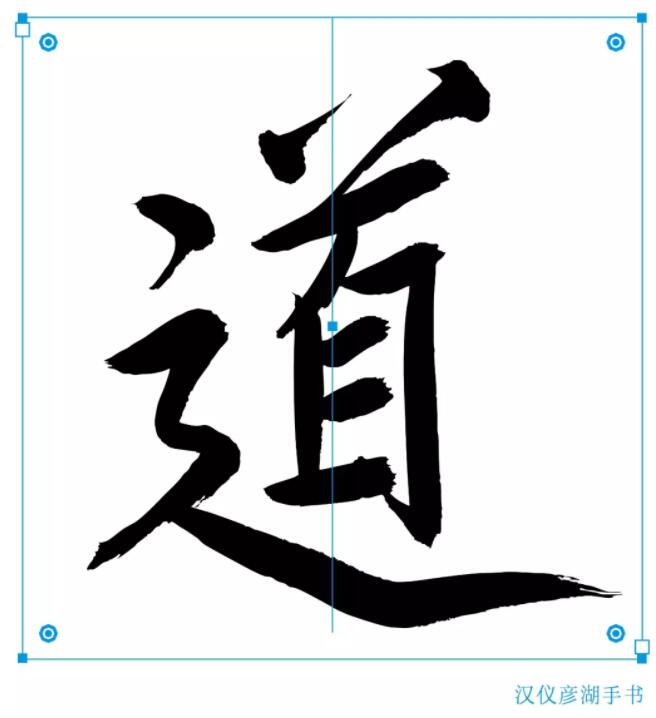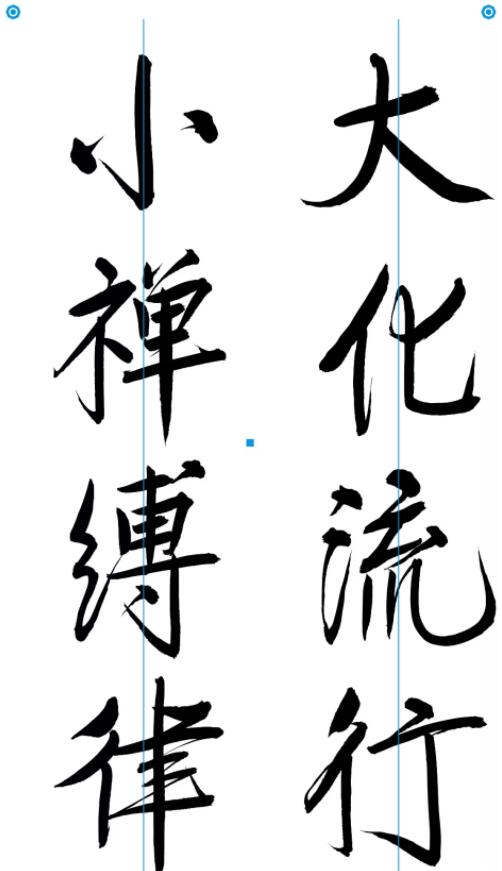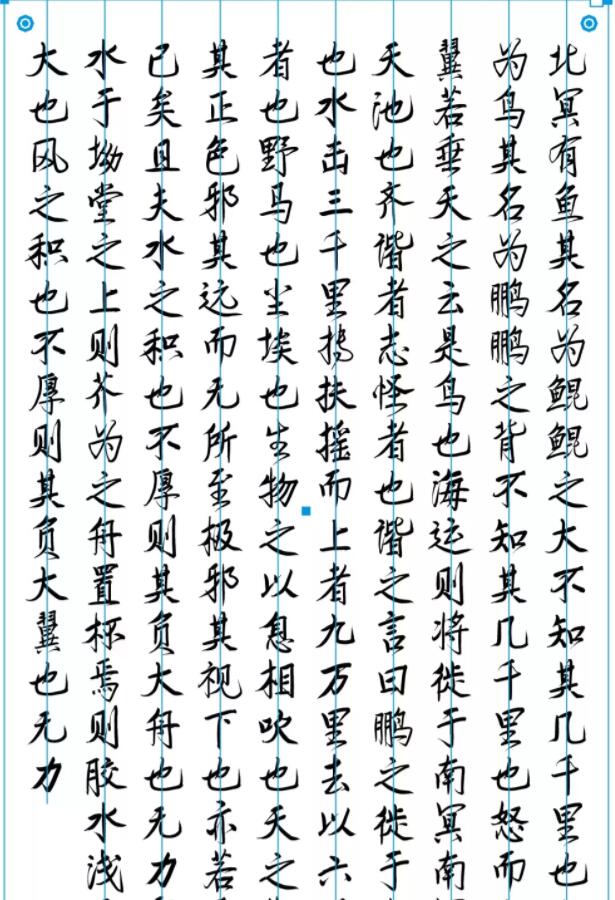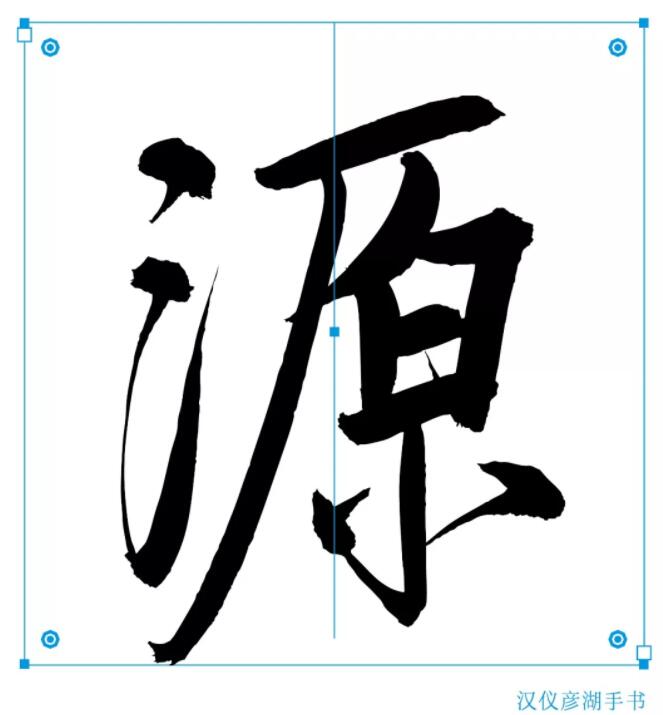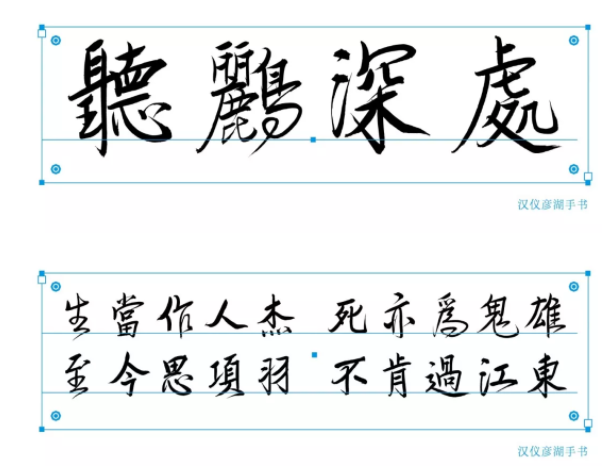
大师系列 | 骨气洞达 —— 刘彦湖书法字库正式上线
汉仪彦湖手书
字体风格: 中国风 / 手写 / 古典 / 文艺 / 休闲
字体设计师介绍
刘彦湖,1960 年3月生于黑龙江省,原籍吉林磐石人。1981年拜罗继祖教授为师,学习书法及古典诗文,后又师从周昔非、王镛两位先生。现为中央美术学院中国画学院教授、硕士研究生导师,中国艺术研究院中国书法院研究员,中国艺术研究院中国篆刻院研究员。